130 Procreate Outline Lettering Brushes
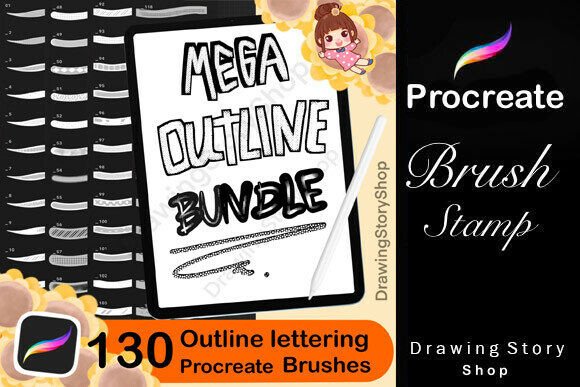
130 Procreate Outline Lettering Brushes – Analyse complète
Vous êtes graphiste, illustrateur ou passionné·e de calligraphie digitale ? Le pack 130 Procreate Outline Lettering Brushes promet de transformer votre iPad en véritable studio de typographie. Voici notre ulasan détaillée, optimisée SEO pour que vous trouviez rapidement toutes les informations essentielles.
- 130 brosses d’esquisse « outline » spécialement conçues pour Procreate.
🎨 Pourquoi ces brushes se démarquent
- Variété extrême : du style graffiti brut aux lettres cursives élégantes, chaque brosse offre une texture unique.
- Contrôle précis grâce aux réglages d’opacité, de taille et de pression, idéal pour les rendus détaillés.
- Optimisé pour le travail en outline : les traits restent nets même après le remplissage de couleur.
💡 Utilisations idéales
- Création de logos typographiques et de titres accrocheurs.
- Design de couvertures d’albums, affiches et flyers.
- Production de digital prints, stickers et contenus pour les réseaux sociaux.
- Intégration dans des projets de scrapbooking numérique et de merchandising.
⭐ Verdict final
Le pack 130 Procreate Outline Lettering Brushes est une investissement incontournable pour quiconque veut enrichir son arsenal créatif sur iPad. Sa diversité, sa facilité d’installation et sa licence flexible en font un outil à la fois professionnel et accessible. Que vous soyez freelance, étudiant·e en design ou simple amateur·rice de calligraphie digitale, ces brushes vous permettront de gagner du temps tout en ajoutant une touche unique à chaque projet.